乍看之下,Dingbat字体似乎用处不大。但是,当您查看各种可用字体时,您会意识到它们可以在您的设计中发挥重要作用。
Dingbats可以用来代替Photoshop笔刷,它们可以用于网页设计中,例如图标,并可以在使用模切Silhouette机器进行制作时使用。您还可以使用Dingbat字体来创建复杂的图案。
如果可以访问Adobe Illustrator,甚至可以使用该程序将Dingbats转换为矢量,然后将其用作图标并用于大规模设计中。 。我们精选了15种免费的Dingbat字体。立即下载!
1。拆分Splat Splodge
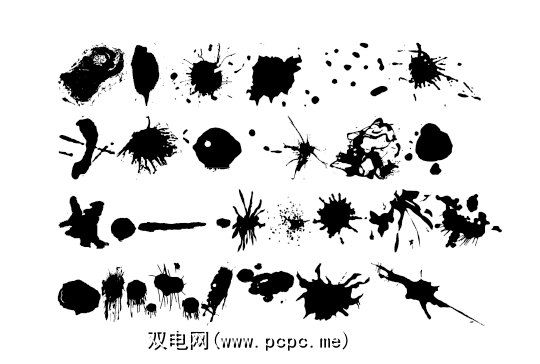
2。 KG香料和框架
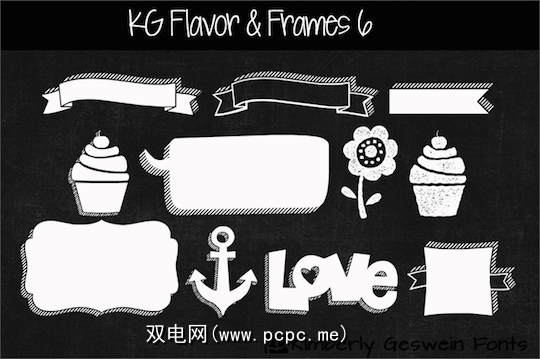
3。 Peoni模式
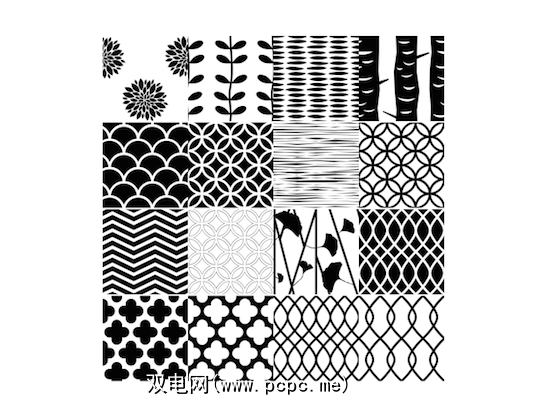
4。莲座丛
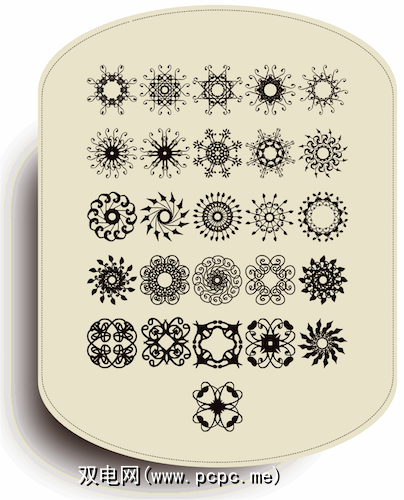
5。 Kalocsai花
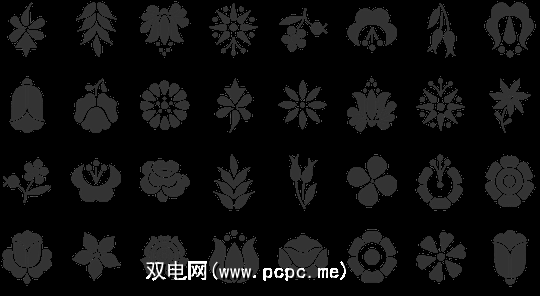
6。 StateFace
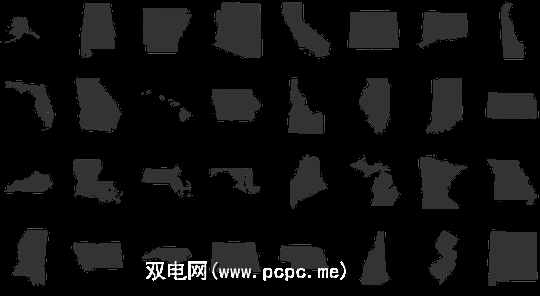
7。糖昏迷
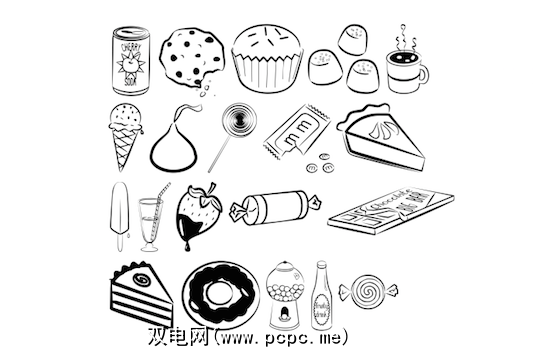
8。 WC售罄
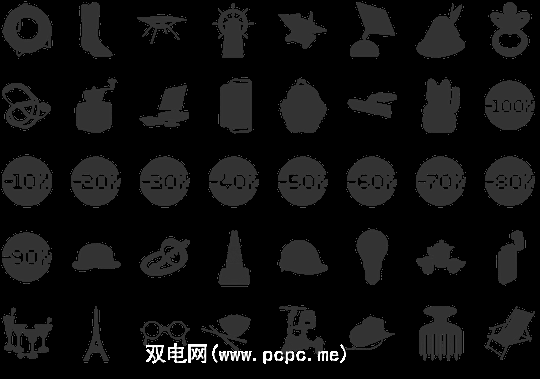
9。氧气
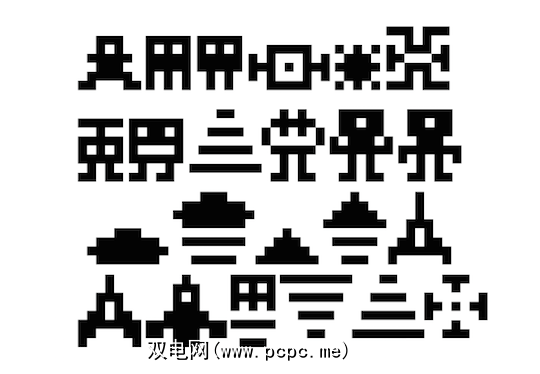
10。网络符号
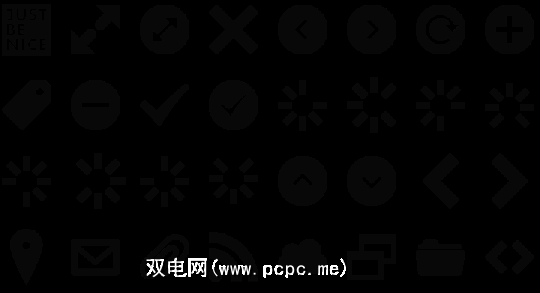
11。 JLS微笑
12。人造雪
13。注意
14。开心节Dingbats
15。 Im Fell Flowers